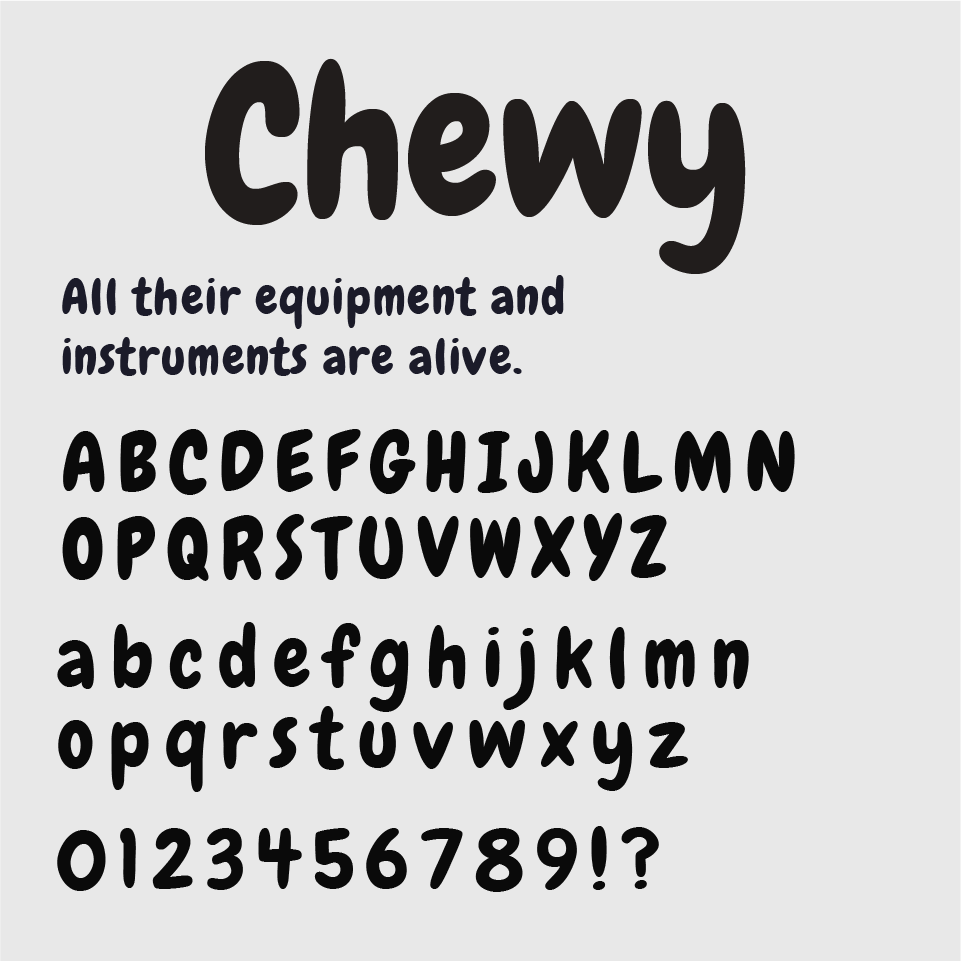
Chewyフォントは、やわらかくもちもちとした丸みのあるシルエットが印象的で、見た目からも親しみやすい手書きフォントです。
角のないフォルムがゆるくて、ポップなので、どこかお菓子やキャラクターっぽさを思わせる愛らしさを感じさせるフォントです。
ポップでにぎやかな雰囲気があり、子ども向けのデザインやアニメーションのタイトル、カジュアルなブランドロゴなどにおすすめです。素直な可愛さが詰まっていて、見ただけで気持ちがゆるむようなフォントです。